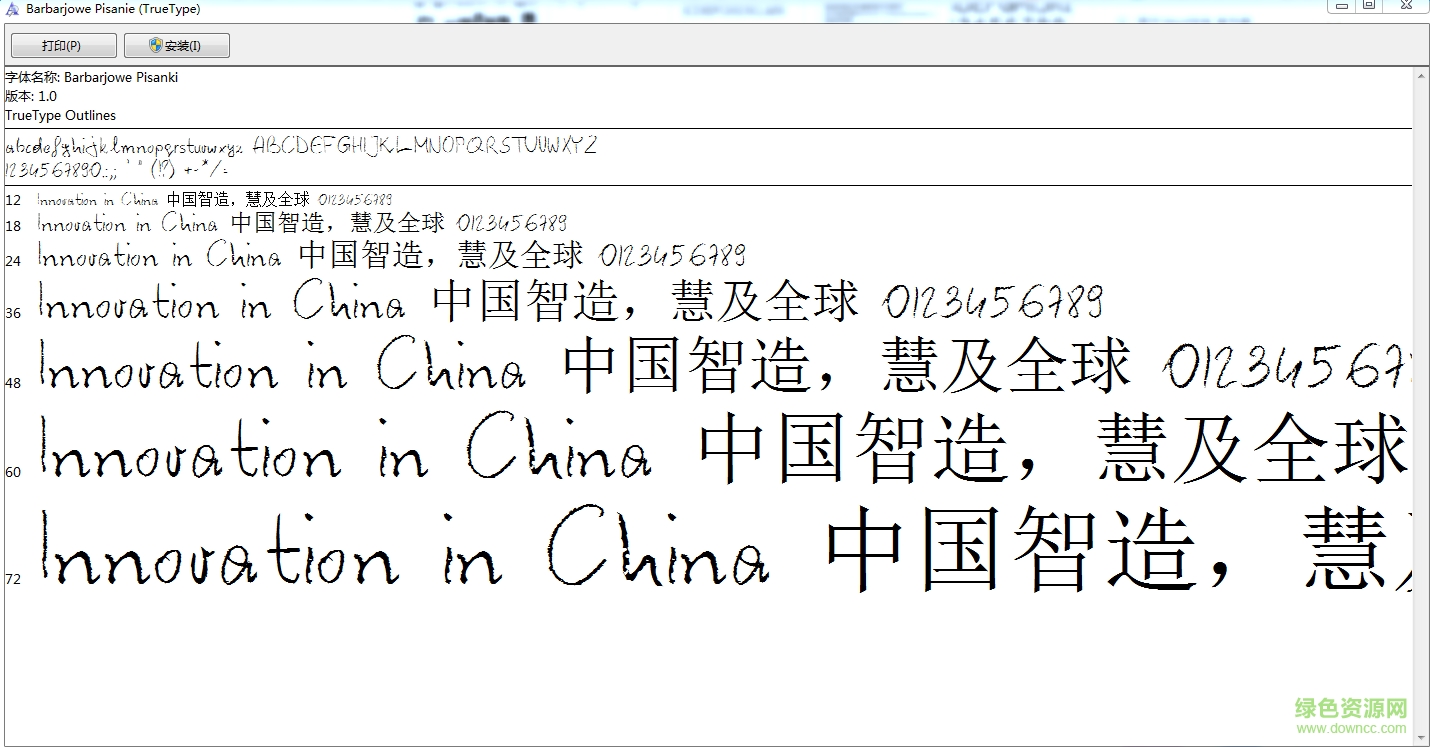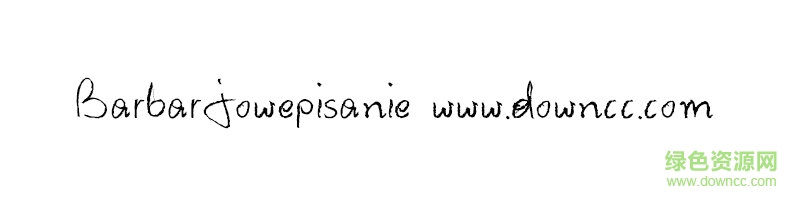
Barbarjowepisanie字體
Barbarjowepisanie是一款比較跳脫的英文字體,字形活潑靈動,打印出來效果非常好,小編已為大家打包整理好了,下載解壓即可使用!有需要的朋友快來綠色資源網(wǎng)下載吧!
Barbarjowepisanie字體展示
Barbarjowepisanie字體